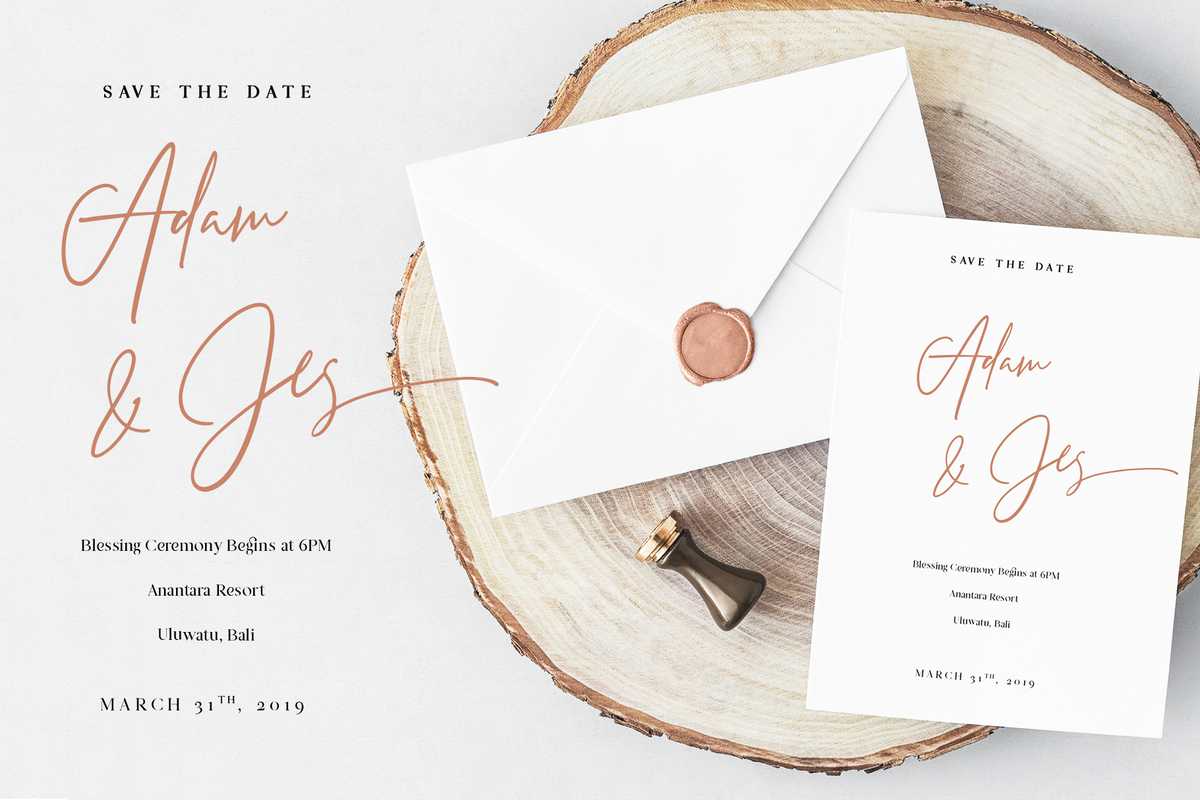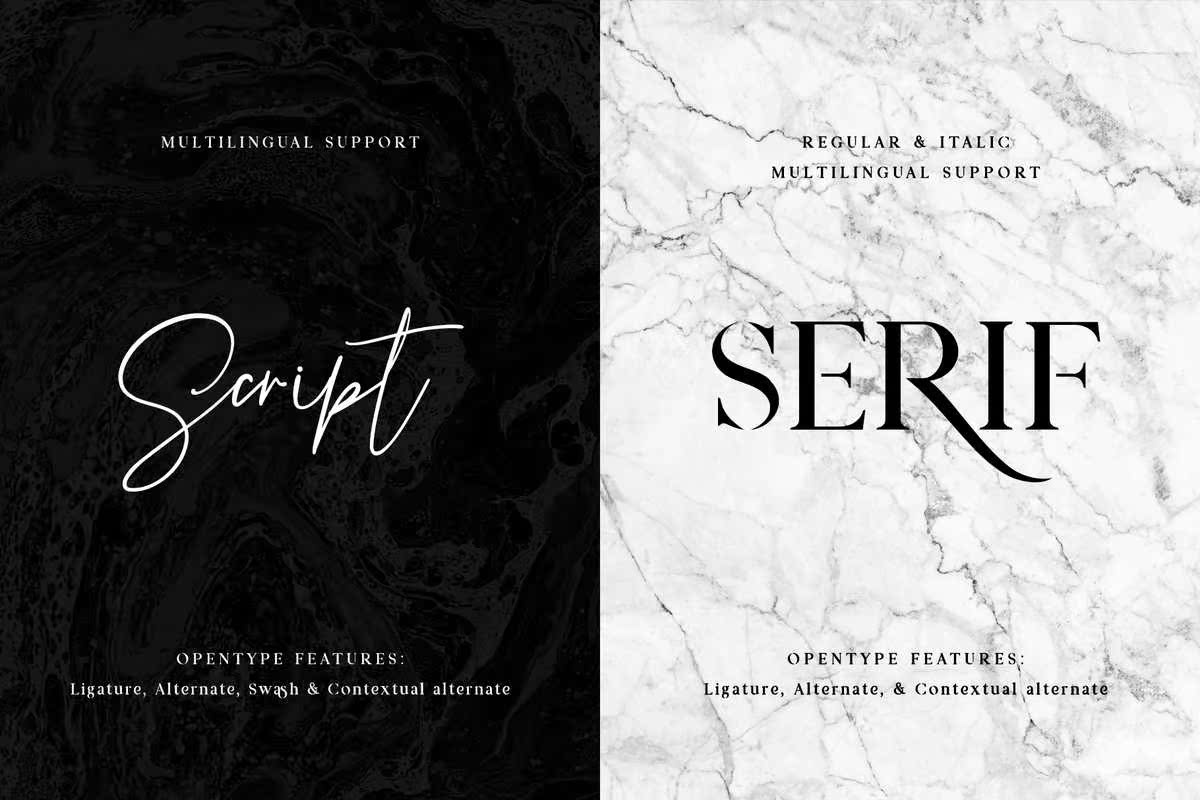
使用AstylisholdSchool系列字体和自由流动的签名,在AncyserifandScriptFont中点击“PrestigeSignature”,即可轻松用于您的设计项目,包括徽标和品牌、婚礼设计、社交媒体、,广告和产品设计。使用AncyserifandScriptFont.和Astylisholdschoolservicen和自由流动的签名,点击Hito“PrestigeSignature”,即可轻松用于您的设计项目,包括徽标和品牌、婚礼设计、社交媒体、广告和产品设计。